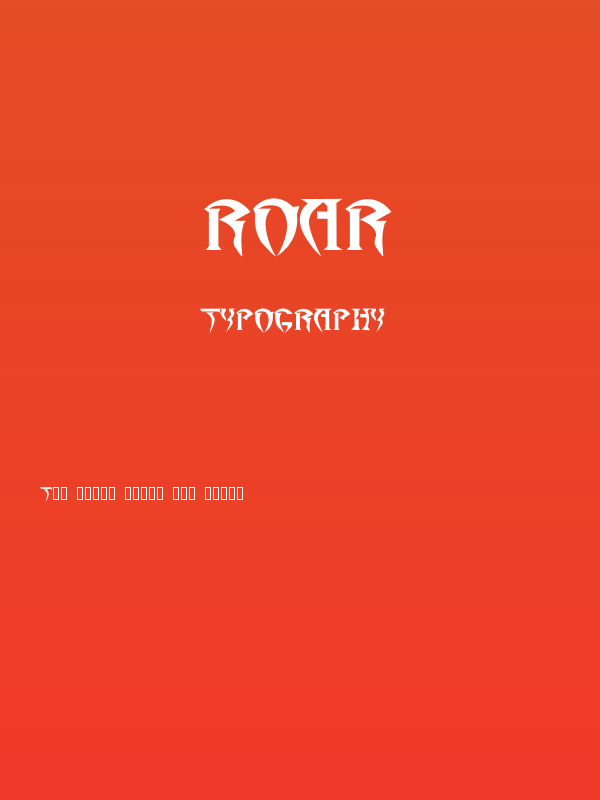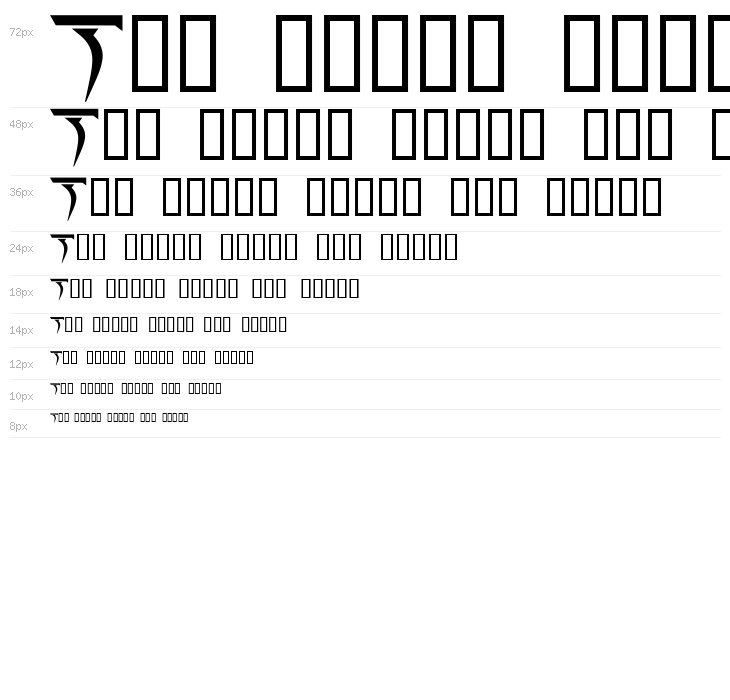
Roar Font
✎ Calligraphic
| Caso de uso | Logos, Headlines |
| Proyectos propuestos | Ideal for projects requiring a strong, authoritative presence such as logos, branding for edgy products, or titles for video games and movies. |